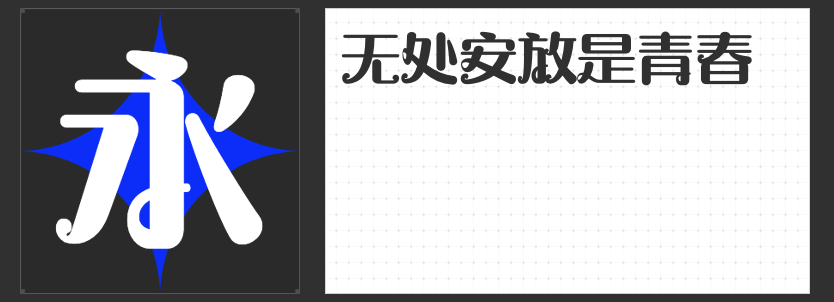
影视设计字体推荐:解锁视觉魅力密码
在影视设计的世界里,合适的字体宛如灵动的音符,能为画面增添独特韵味,传递情感与氛围。今天就为大家推荐四款适用于影视设计的优质字体。
一、字恋狂漫野 摇风
字恋狂漫野 摇风以手写感为基石,打造出别具一格的直线字体。其结构张弛有度,布白空间通透,仿佛呼吸般自然。不同字型大小错落,细微的变化带来强烈的节奏感,让版面瞬间活跃起来。笔画设计简洁却不失灵动,去钩处理与“断开”特点巧妙融合,以直线组合变化为主,灰度均匀,在保持整体协调的同时,又不失个性与变化,无论是文艺片中的诗意表达,还是青春片里的活力呈现,它都能轻松驾驭。
二、励字造桃气圆 大粗
励字造桃气圆 大粗是一款充满手写感的圆体。字型上松下紧,重心略低,结构松弛灵活,变化多样,就像灵动的小精灵。整体笔形圆润饱满,舒展流畅,给人以柔和、亲切之感。统一的笔画设计,折笔处内外圆角兼备,圆形元素的巧妙运用,丰富了视觉效果。笔画间的“断开”处理,更增添了轻快的整体风格,在儿童题材影视或温馨治愈类影视中,能营造出欢快、活泼的氛围。
三、字恋狂嗨玩简
字恋狂嗨玩简有着粗壮的笔画和方块字形,如同积木般可爱。重心靠下的设计,让整个字体透露出一种笨拙又俏皮的气质。在喜剧片或奇幻冒险类影视中,使用这款字体能为画面增添一份童趣与欢乐,使观众更容易沉浸在轻松愉悦的氛围里。
四、励字摩登圆简
励字摩登圆简堪称字体中的“多面手”,富有装饰意趣,风格多变。可复古可新潮,可严谨又可浪漫,在儿童风画面中也能展现出独特的魅力。它适用于多种风格的包装、书、报、杂志、电商等装饰用字,在影视设计中,无论是海报标题还是片头字幕,都能凭借其出色的视觉排版效果,吸引观众的目光。
这四款字体各具特色,能为影视设计带来无限可能,让你的作品在视觉上脱颖而出。